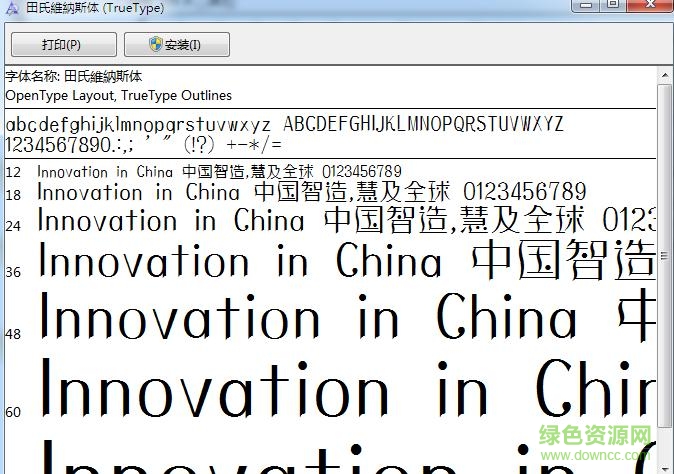
田氏維納斯字體
田氏維納斯體是一款非常實用的藝術(shù)字體,可以輕松的將你想要的字變成微帶波浪形的字體,非常的有意思,喜歡的朋友歡迎下載使用!
田氏維納斯體簡介
田氏維納斯體是田氏字體中的一款非常有特色的字體,該字體將漢字筆畫中的捺筆畫全部換成了可愛的小圓點,整體看上去非常的q萌!
田氏維納斯體